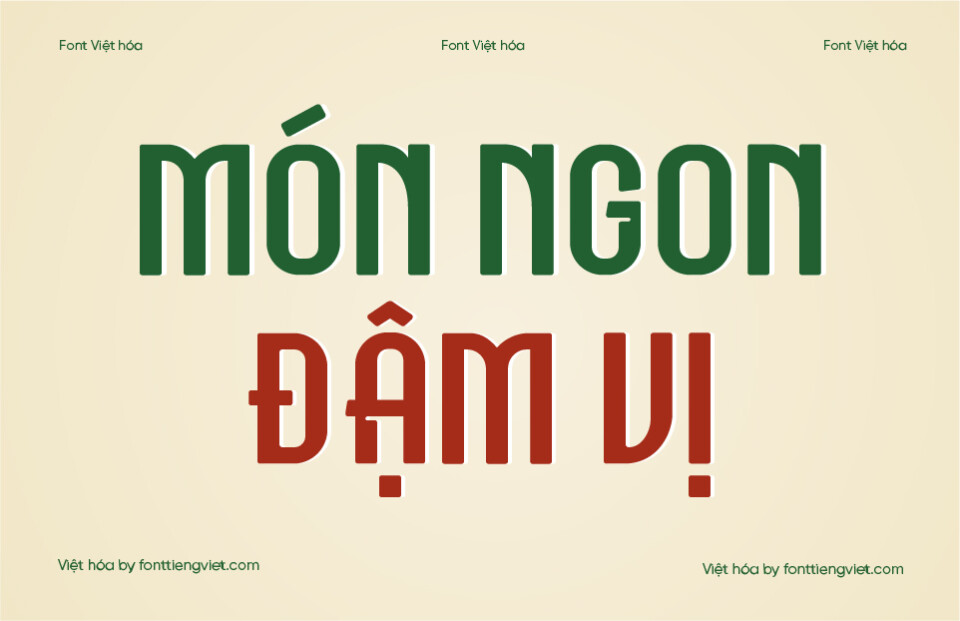
Tải Font Việt hóa 1FTV VIP Meholrax – Font chữ thiết kế sang trọng và hiện đại
Giới thiệu về Font Việt hóa 1FTV VIP Meholrax trong thiết kế đồ họa
Trong thế giới sáng tạo, việc lựa chọn một bộ Font Chữ phù hợp đóng vai trò quyết định đến sự thành công của một sản phẩm truyền thông. Font Việt hóa 1FTV VIP Meholrax là một lựa chọn xuất sắc dành cho những ai đang tìm kiếm sự phá cách nhưng vẫn giữ được nét tinh tế. Đây là bộ font mang phong cách hiện đại, được tối ưu hóa hoàn toàn về dấu tiếng Việt, giúp người dùng dễ dàng sử dụng trong các phần mềm thiết kế phổ biến mà không lo lỗi hiển thị. Với đường nét sắc sảo và bố cục cân đối, Meholrax mang lại cảm giác chuyên nghiệp cho mọi dự án.
Tại sao nên sử dụng Font Việt hóa 1FTV VIP Meholrax cho dự án của bạn?
Font Việt hóa 1FTV VIP Meholrax không chỉ đơn thuần là các ký tự, mà còn là một công cụ truyền tải cảm xúc mạnh mẽ. Bộ font này sở hữu các đặc điểm nổi bật như: đường nét thanh thoát, khả năng hiển thị tốt trên cả nền tảng kỹ thuật số và in ấn. Đối với các bạn học sinh hay thầy cô giáo, việc áp dụng font chữ này vào bài thuyết trình hoặc thiết kế báo tường sẽ giúp nội dung trở nên thu hút và dễ theo dõi hơn. Sự kết hợp giữa tính thẩm mỹ và công năng đã biến Meholrax thành một trong những bộ font được săn đón nhất hiện nay.
Bạn có thể ứng dụng Font Việt hóa 1FTV VIP Meholrax vào rất nhiều lĩnh vực khác nhau như thiết kế logo, banner quảng cáo, hay bìa sách giáo khoa. Với tính linh hoạt cao, font chữ này phù hợp cho cả tiêu đề chính lẫn các đoạn văn bản ngắn cần tạo điểm nhấn. Để bắt đầu sáng tạo, bạn chỉ cần tải bộ font này về và cài đặt trực tiếp vào hệ thống máy tính. Việc sử dụng các font đã được Việt hóa kỹ lưỡng như Meholrax sẽ giúp tiết kiệm thời gian chỉnh sửa và đảm bảo tính thẩm mỹ cao nhất cho tác phẩm của bạn.